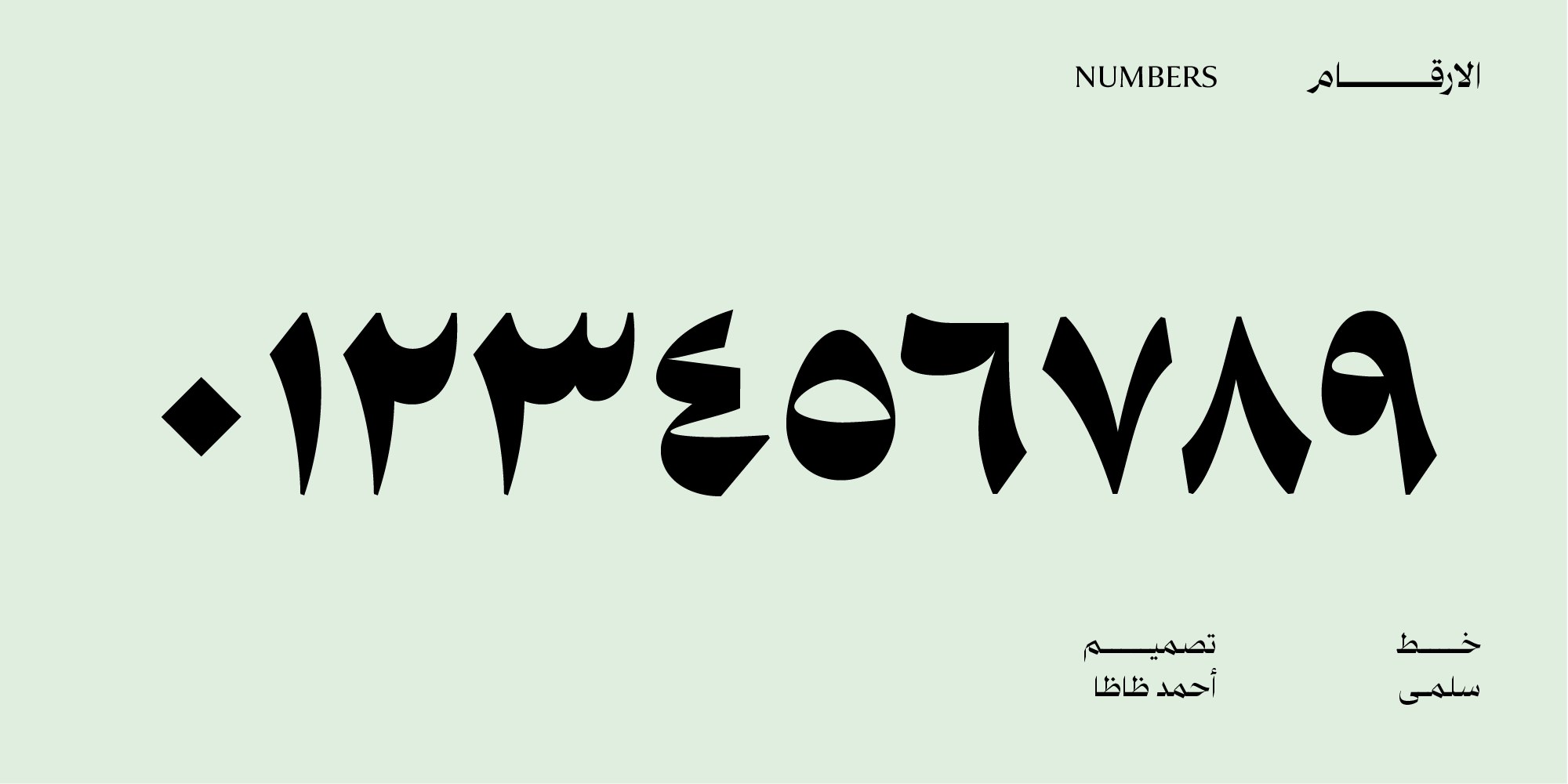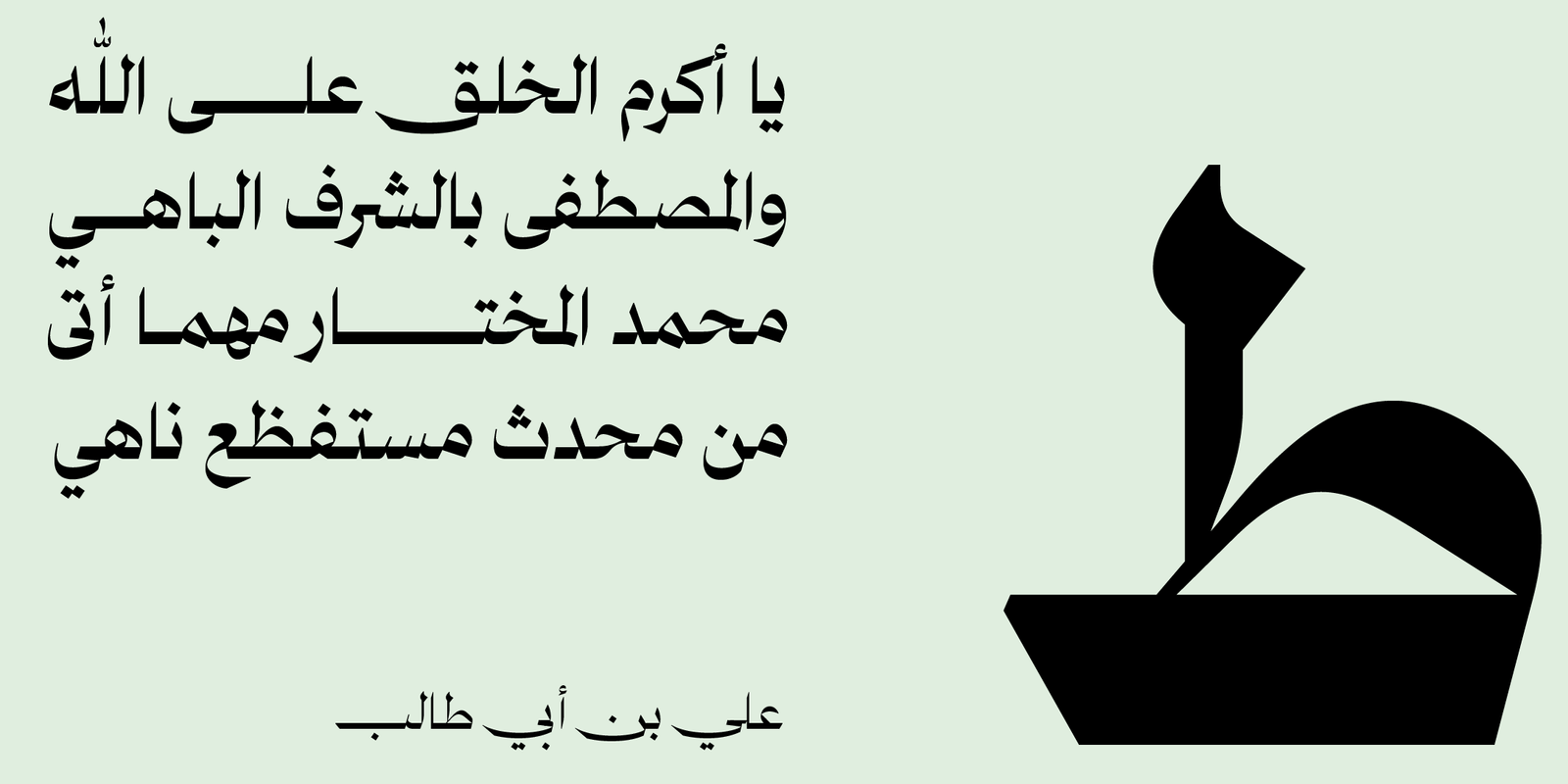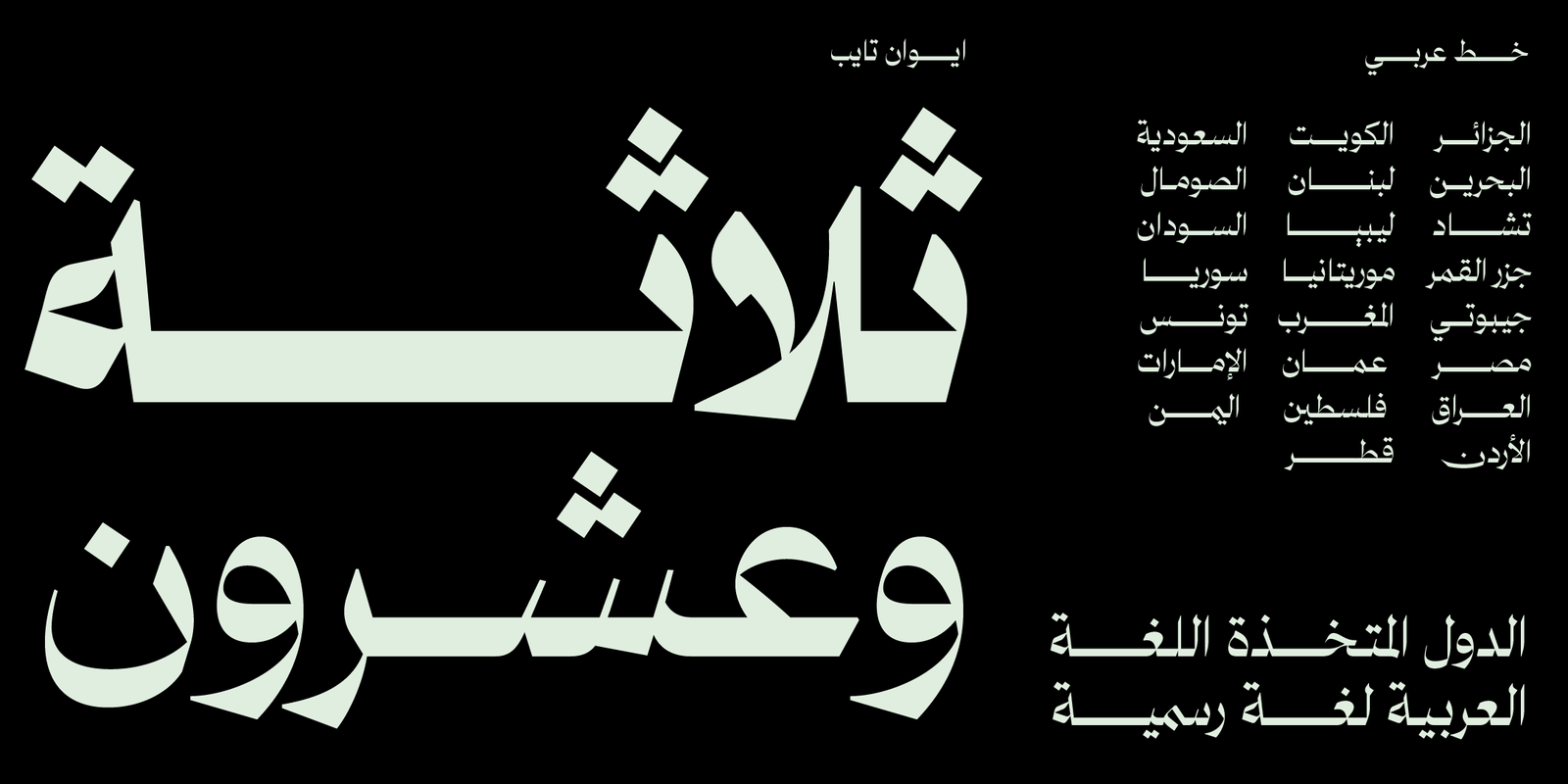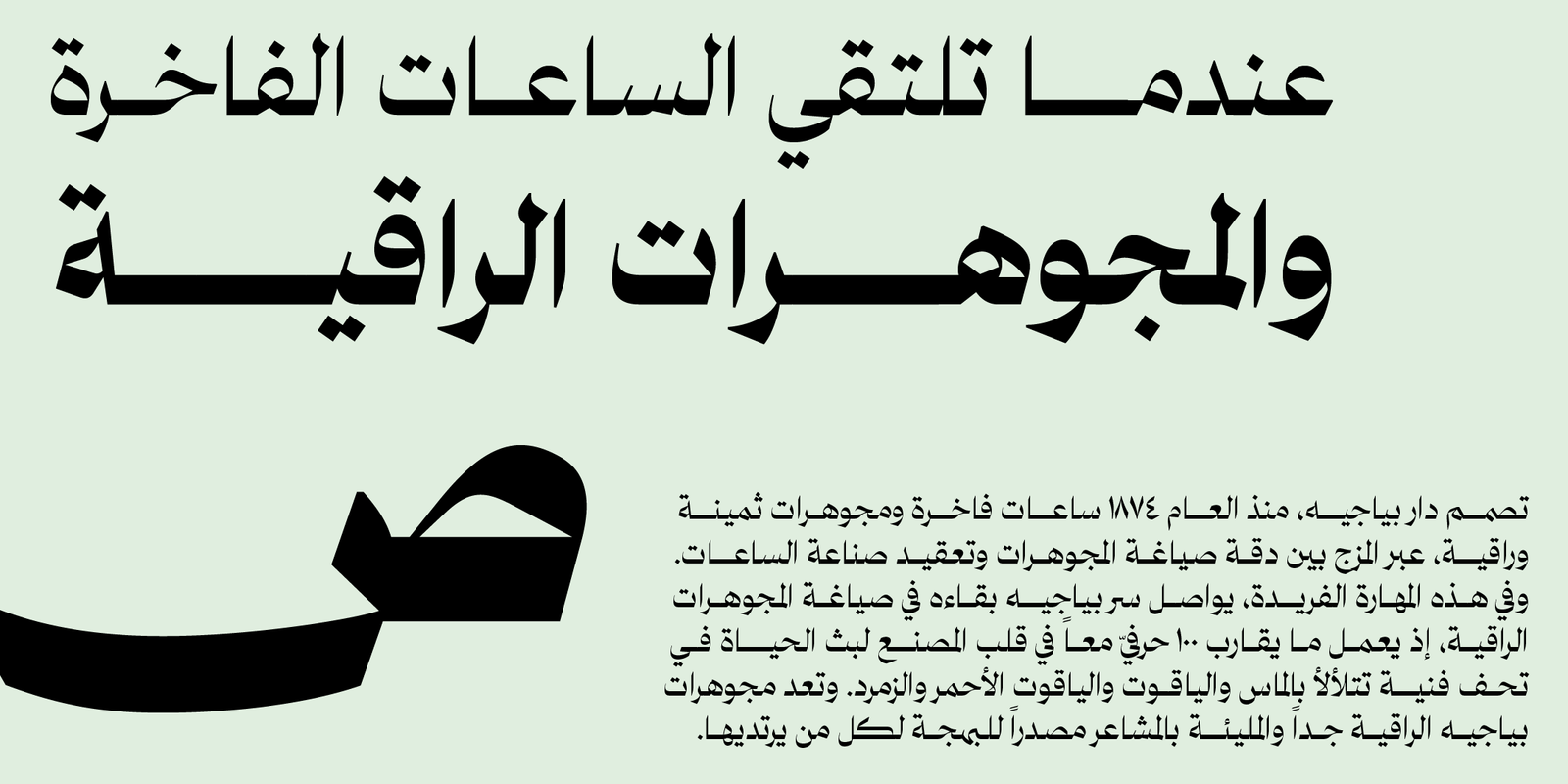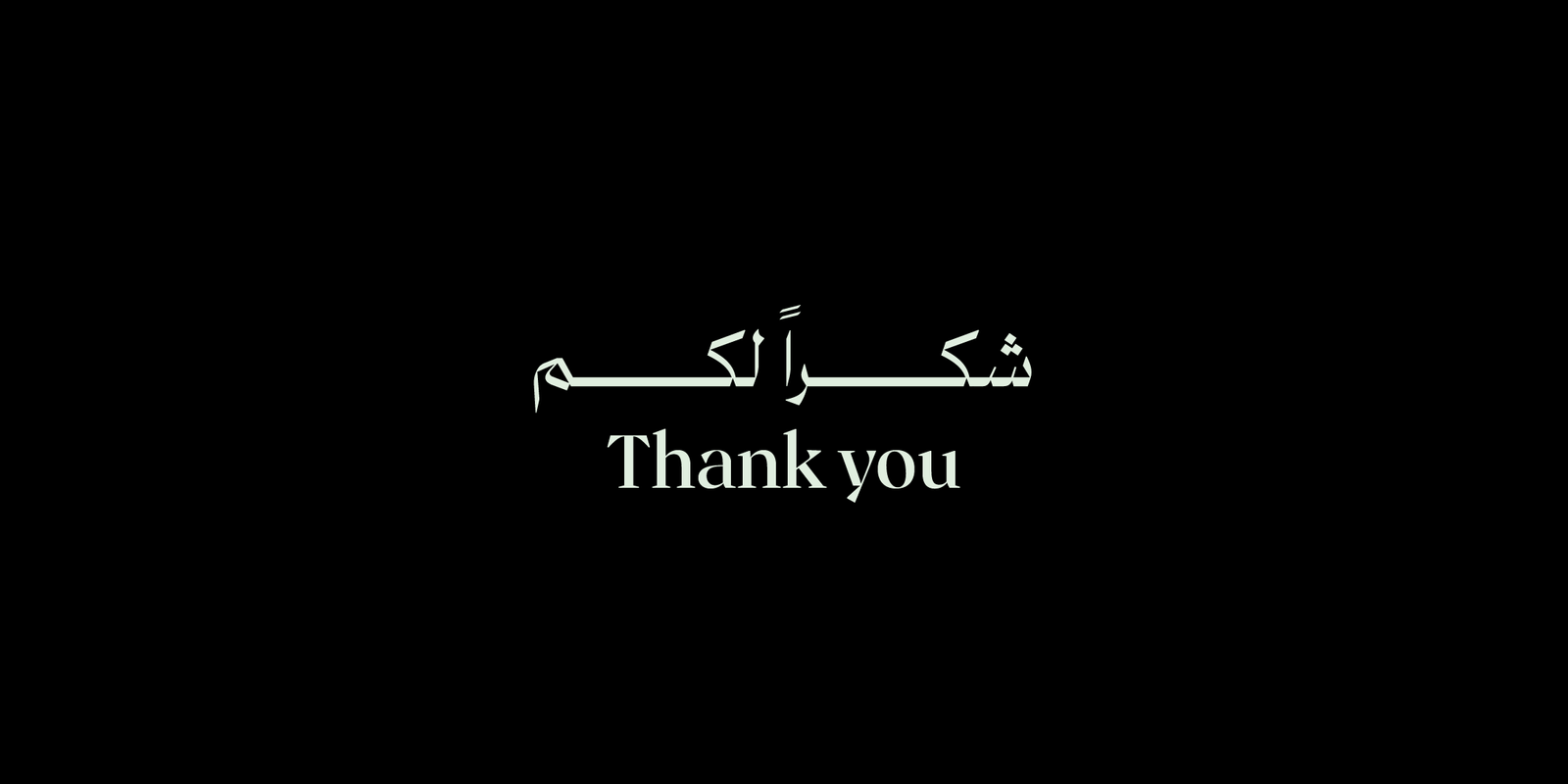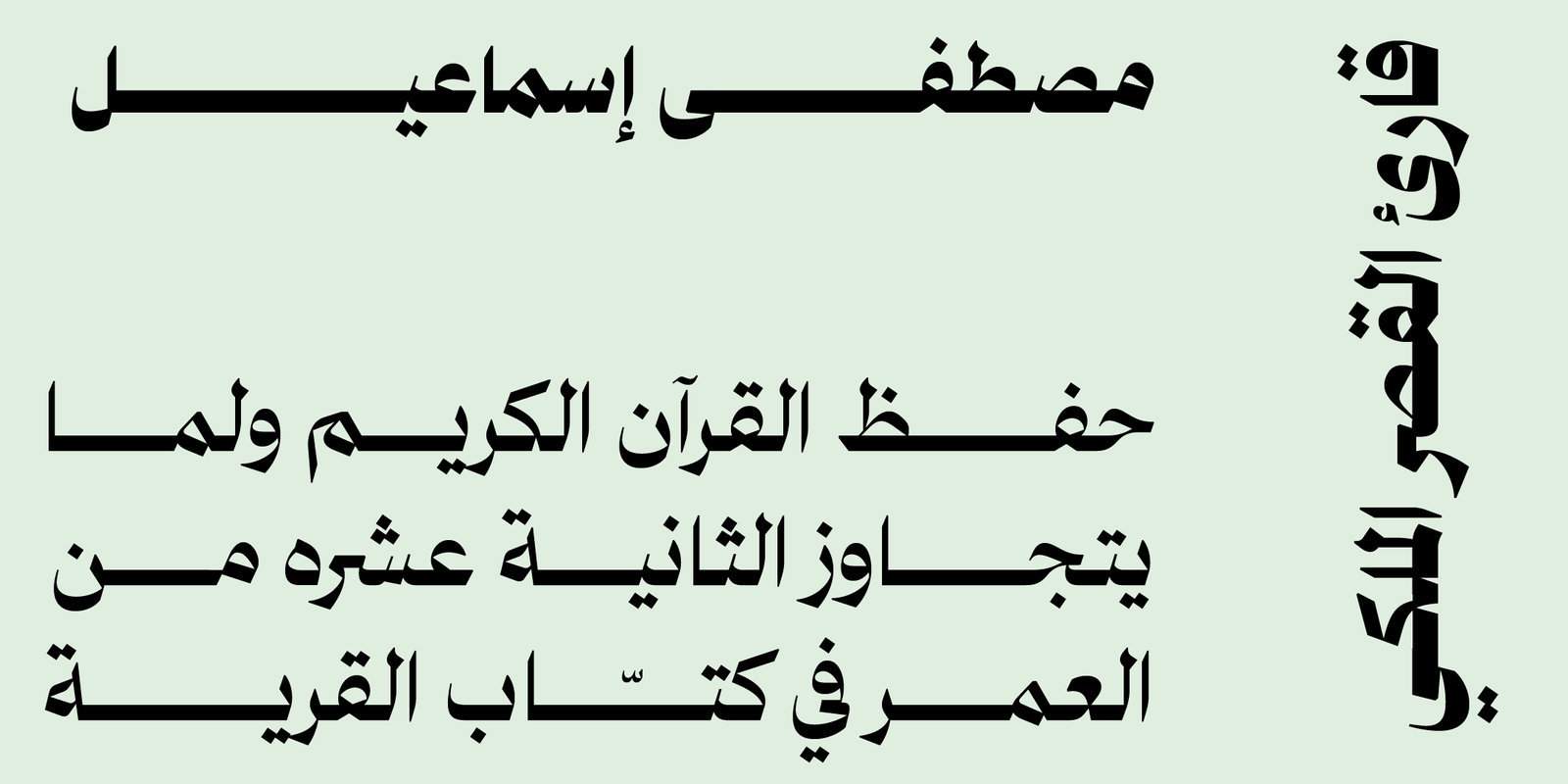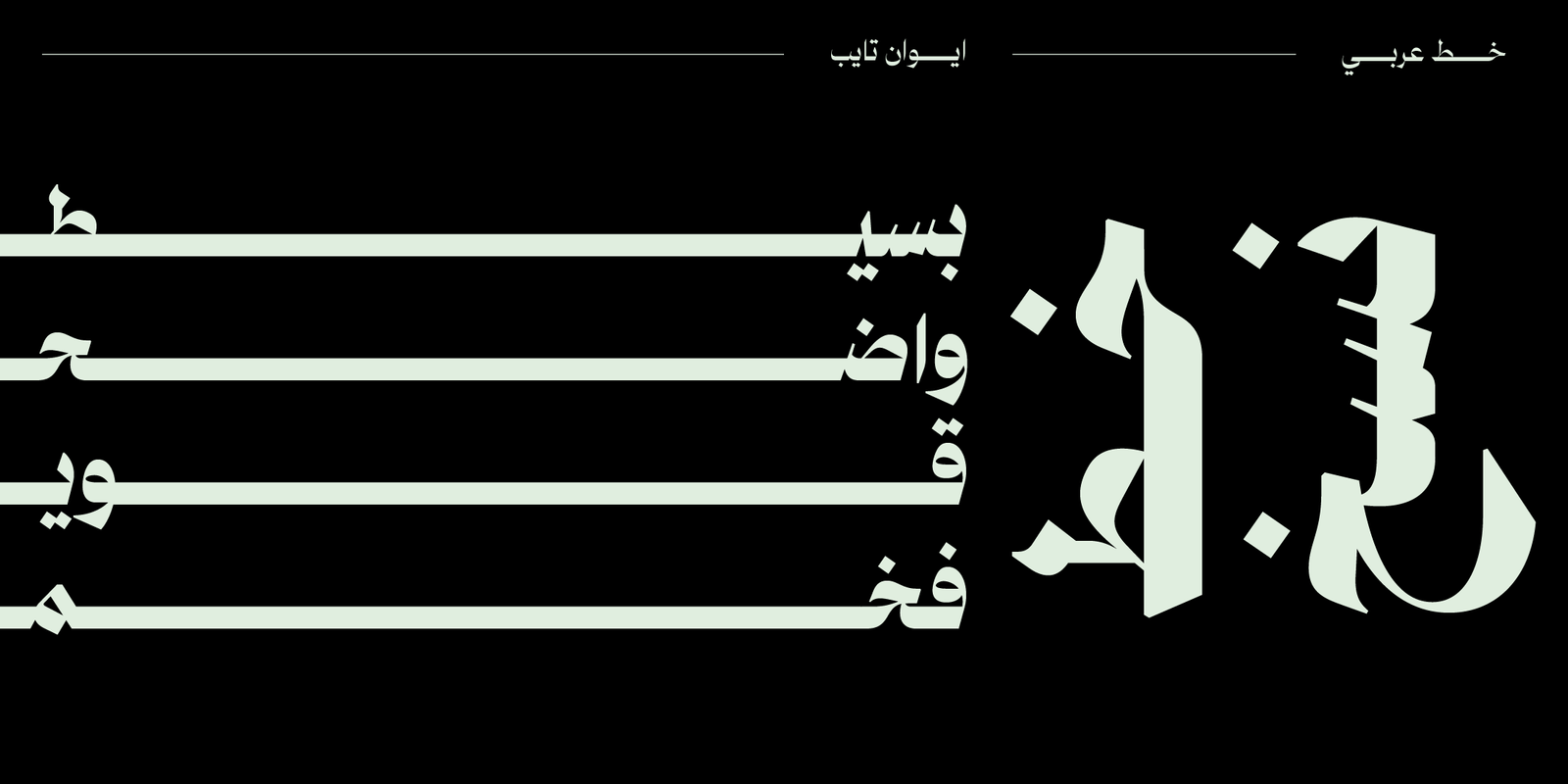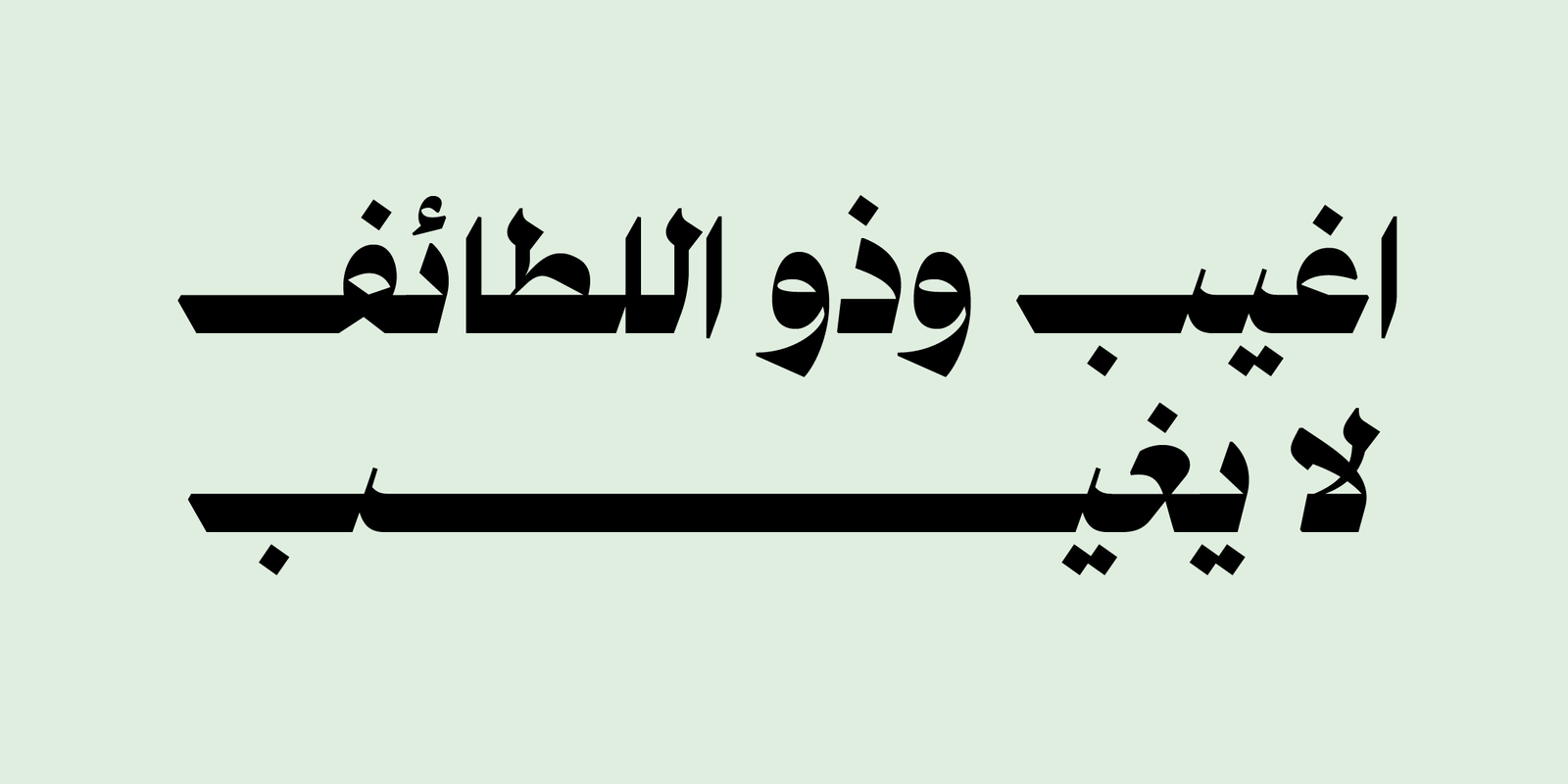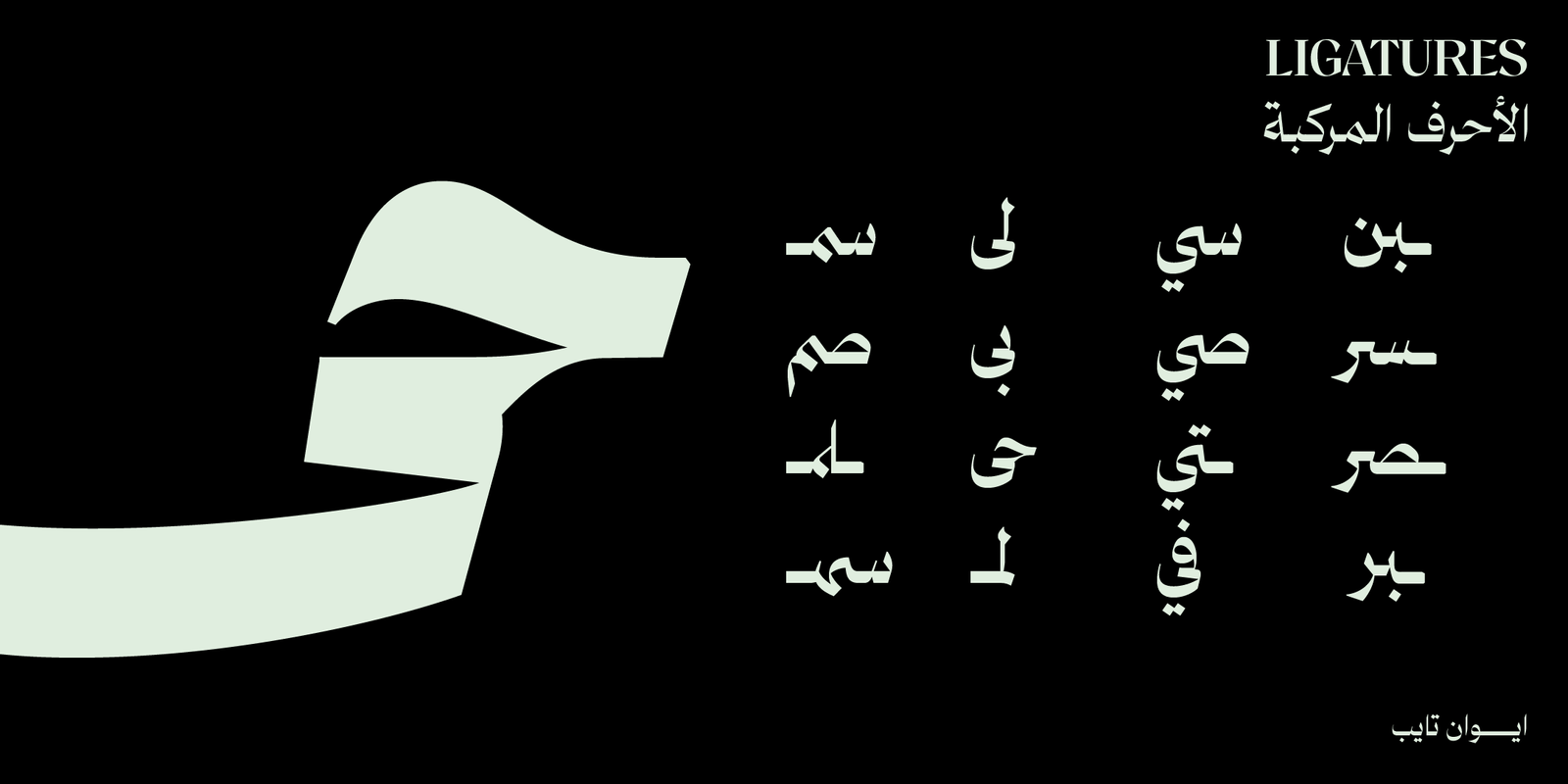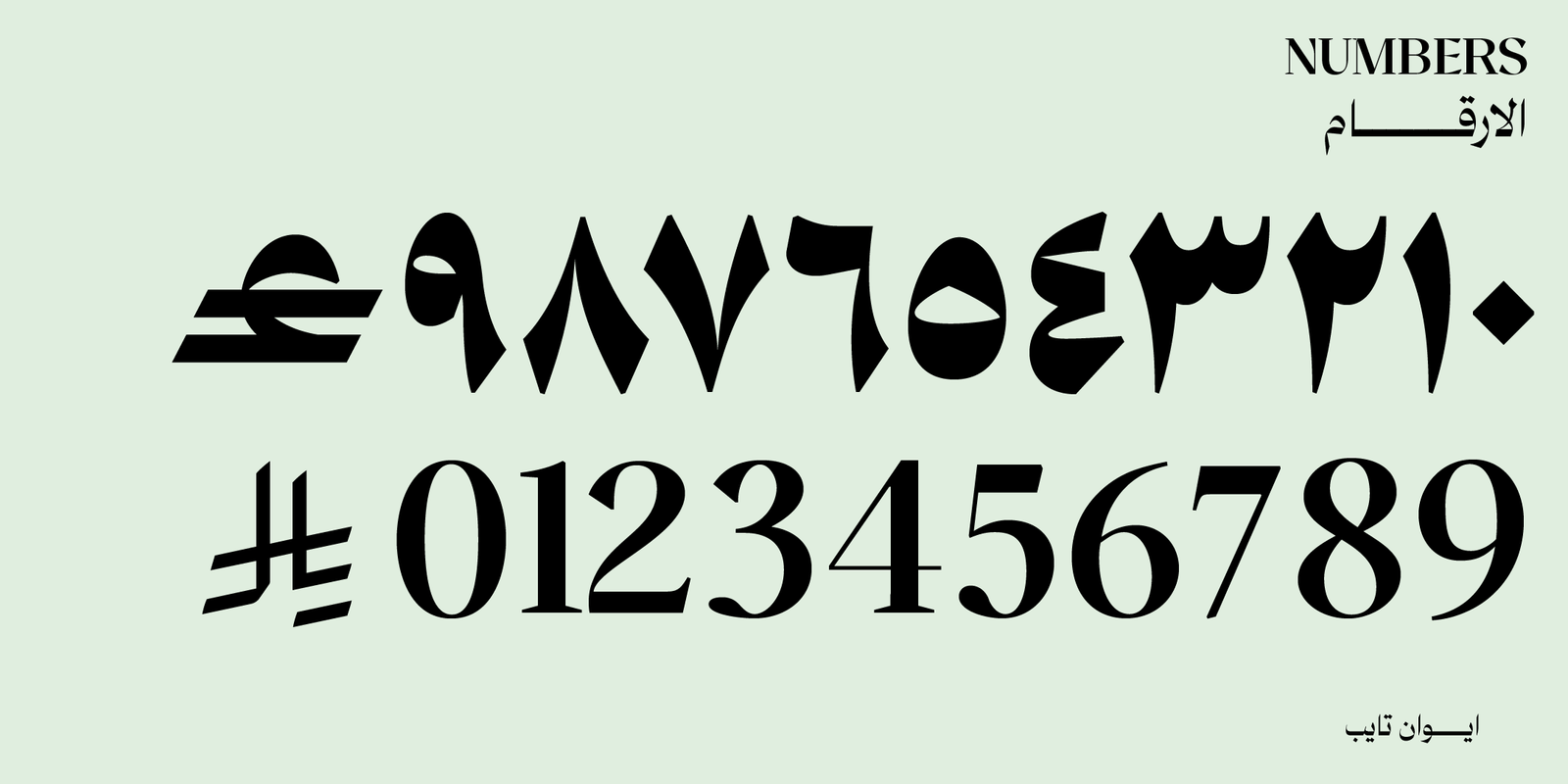
سلمى هو خط عربي طباعي حديث مستوحى من أسلوب النسخ المسطري. يختلف عن الخطوط التقليدية بتباينه العالي ووصلاته الجديدة بين الحروف ، مما يخلق جمالية لافتة للنظر تجعل أي نص بارزًا. تجعل خطوطه الجريئة وجاذبيته الخالدة من سلمى خط مثاالى للعناوين والطباعة ، بالإضافة إلى مشاريع التصميم الأخرى.
يأتي في 5 أوزان تتراوح من الخفيف إلى الأسود ، مع ميزات OpenType.
المظهر الفريد لسلمى يجعله مثالي للشعارات والعلامات التجارية التي تتطلب لمسة مميزة. بفضل وجوده القوي على  الوسائط المختلفة مثل المنشورات المطبوعة أو شاشات العرض الرقمية ، يمكن استخدام هذا الخط متعدد الاستخدامات لإنشاء تصاميم مؤثرة.
مميزات خط سلمى:
يتضمن الخط العديد من مزايا OpenType التي تضفي عليه مرونة وتنوعًا في الاستخدام، مثل:
• أحرف مرسلة (تُفعَّل بإضافة “ءء” بعد الحرف)
• أحرف مركّبة تُحسّن سلاسة التراكيب وتناسق النص.
• خمسة أوزان كاملة تمنح مرونة واسعة في الاستخدام الطباعي.
• يدعم رمز الريال السعودي والريال العُماني ،ويتم تفعيلهما تلقائيًا عند كتابة الاختصارات: ر.س للريال السعودي ر.ع للريال العُماني
اللغات: العربية لاتيني
الأوزان: ٥ أوزان